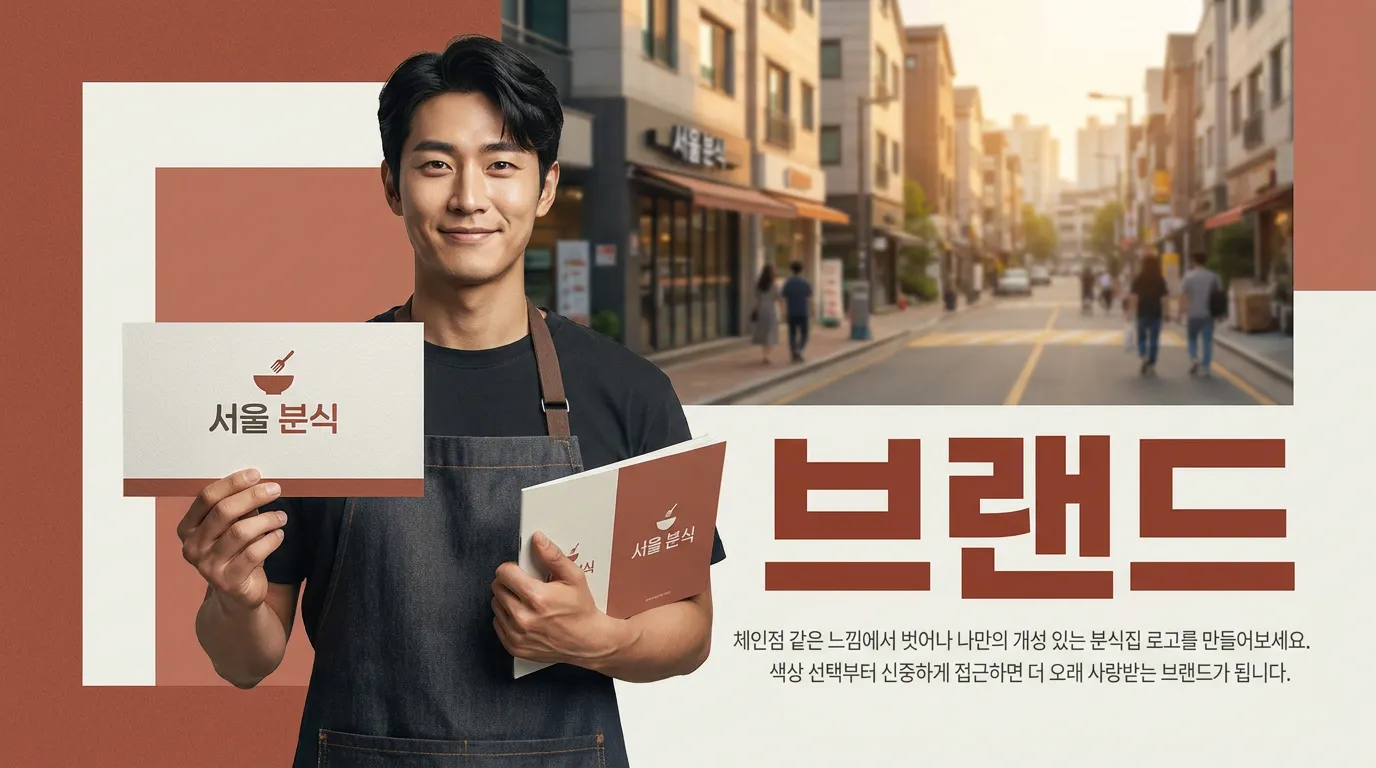
로고 색상 조합, 분식집은 빨간색보다 글자 모양이 먼저입니다
분식집 로고 디자인에서 떡볶이 색보다 먼저 잡아야 할 폰트, 심볼, 메뉴 확장 기준 5가지를 실무 기준으로 정리했습니다.
떡볶이 사진은 맛있는데, 가게 이름만 보면 어디서 본 체인점처럼 느껴질 때가 있습니다.
왜 빨간색보다 글자 모양을 먼저 봐야 할까요?
사장님이 처음 고르는 건 보통 색입니다. 매운맛이니까 빨강, 치즈니까 노랑. 그런데 현장에서 보면 오래 버티는 분식집 로고는 색보다 글자 뼈대가 먼저 잡혀 있습니다.
이렇게 하세요. 가게 이름을 3m 밖, 휴대폰 썸네일, 영수증 상단 크기로 줄여서 먼저 보세요. 이때 읽히지 않으면 색을 아무리 맛있게 써도 소용없습니다.
귀여운 손글씨면 무조건 친근해 보일까요?
분식집 로고에서 손글씨체를 많이 씁니다. 문제는 ‘정겨움’과 ‘아마추어 같음’이 한 끗 차이라는 점입니다. 획이 너무 흔들리면 맛집보다 동네 행사 포스터처럼 보입니다.
이렇게 하세요. 받침이 많은 이름은 둥근 고딕 계열로, 짧고 리듬 있는 이름은 손맛이 있는 서체로 가세요. 예를 들어 ‘왕김밥떡볶이’처럼 글자가 긴 이름은 장식보다 간격 정리가 먼저입니다.
제가 분식 브랜드 시안을 볼 때도 첫 체크는 예쁨이 아닙니다. ‘김’, ‘볶’, ‘집’ 같은 글자가 뭉개지지 않는지 봅니다. 분식집은 메뉴가 많아서 로고가 메뉴판, 스티커, 배달 봉투 안에서 계속 작아지기 때문입니다.
심볼은 떡볶이 그릇이면 끝일까요?
떡볶이 그릇, 김밥 단면, 젓가락. 다 맞는 소재입니다. 그런데 다 같이 쓰면 아무것도 남지 않습니다. 손님 머리에 남는 건 하나여야 합니다.
이렇게 하세요. 심볼은 메뉴 하나가 아니라 ‘먹는 장면’ 하나로 잡으세요. 말린 김밥의 원, 소스가 튄 점, 젓가락으로 집은 떡 한 줄. 이렇게 단순해야 배달앱 아이콘에서도 버팁니다.
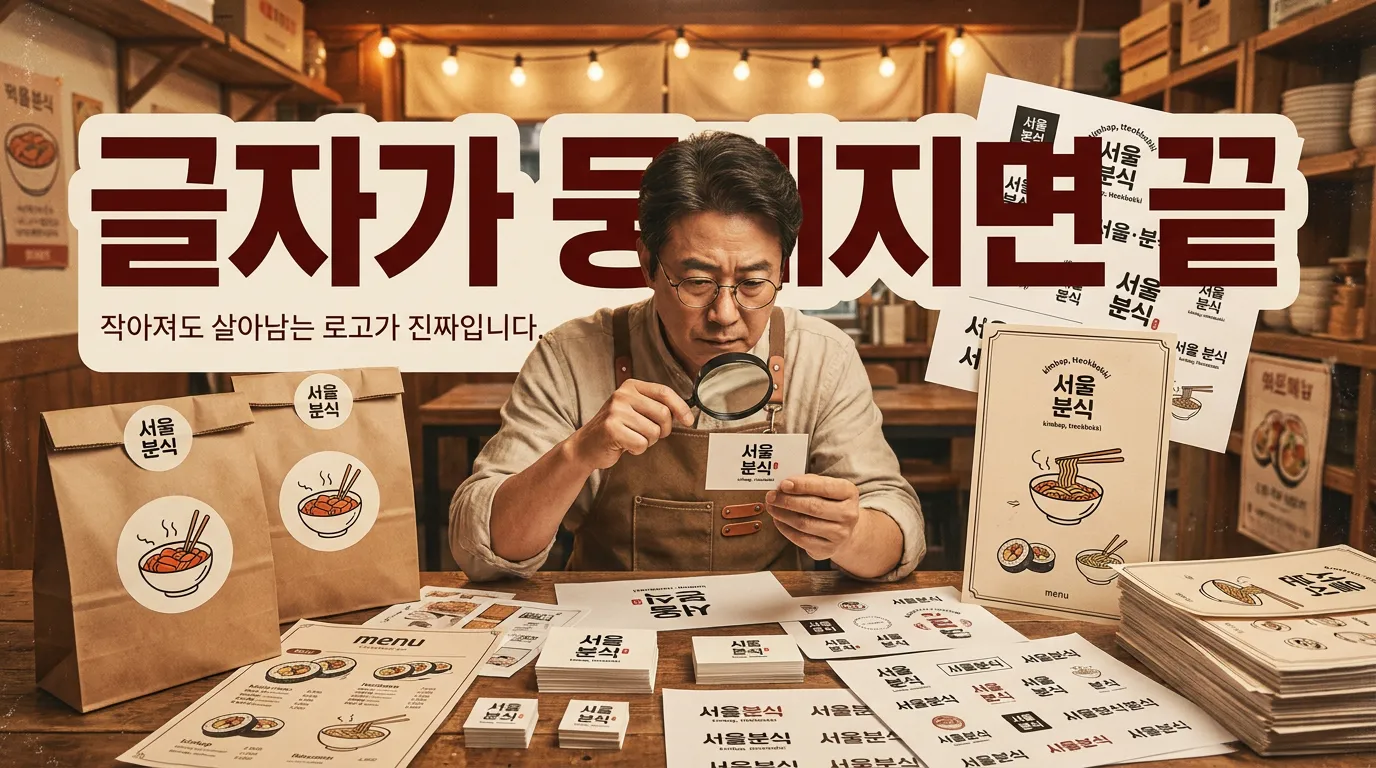
메뉴가 늘어도 무너지지 않는 로고는 뭘 다르게 만들까요?
처음엔 떡볶이만 팔아도, 잘되면 김밥·튀김·어묵·덮밥이 붙습니다. 이때 로고가 떡볶이 냄비 하나에만 묶여 있으면 확장이 답답해집니다.
이렇게 하세요. 로고 안에는 대표 메뉴를 넣되, 브랜드 말투는 더 넓게 잡으세요. ‘매운 떡볶이’보다 ‘퇴근길 한 그릇’, ‘학교 앞 한입’ 같은 정서가 오래 갑니다.
마크에서 분식집 로고를 잡을 때도 색상표보다 먼저 하는 일이 있습니다. 이름의 속도, 글자 무게, 심볼의 반복 가능성을 한 장에 놓고 보는 일입니다. 간판은 그다음입니다. 로고가 서야 간판도, 메뉴판도, 포장지도 덜 흔들립니다.
마지막 색은 몇 개만 남겨야 할까요?
분식집이라고 빨강, 노랑, 초록, 검정, 흰색을 다 쓰면 맛있어 보이는 게 아니라 싸 보일 수 있습니다. 색이 많을수록 기억은 흐려집니다.
이렇게 하세요. 주색 1개, 보조색 1개, 배경색 1개로 시작하세요. 그리고 흑백 로고로 먼저 통과시킨 뒤 색을 얹으세요. 흑백에서 먹히는 로고가 빨간색을 입었을 때 더 강합니다.